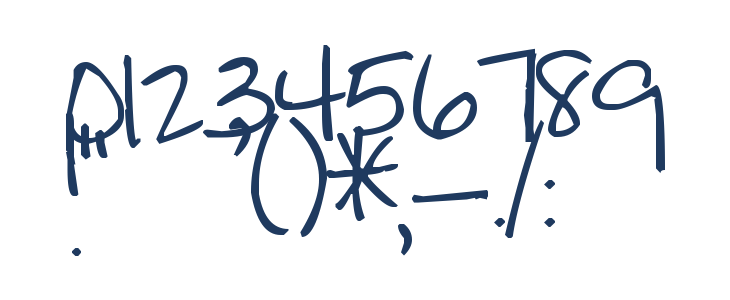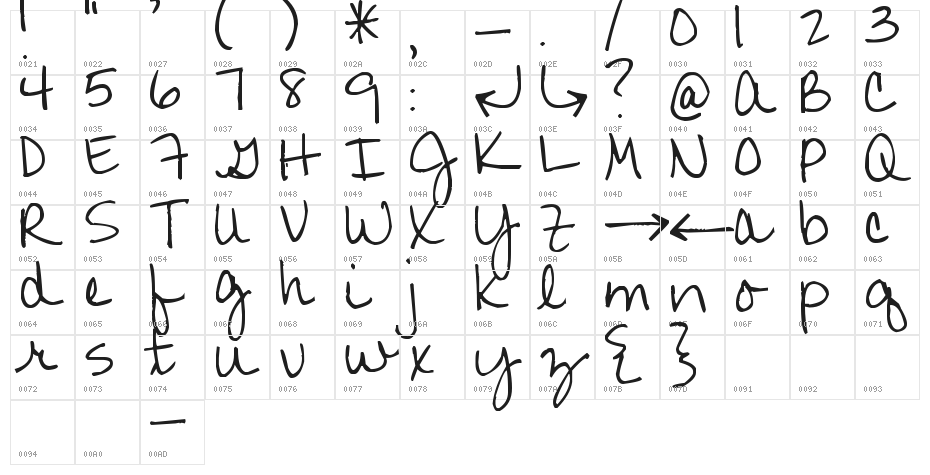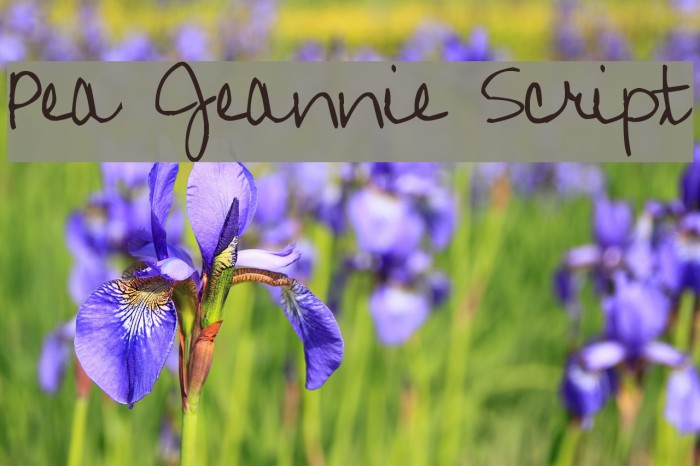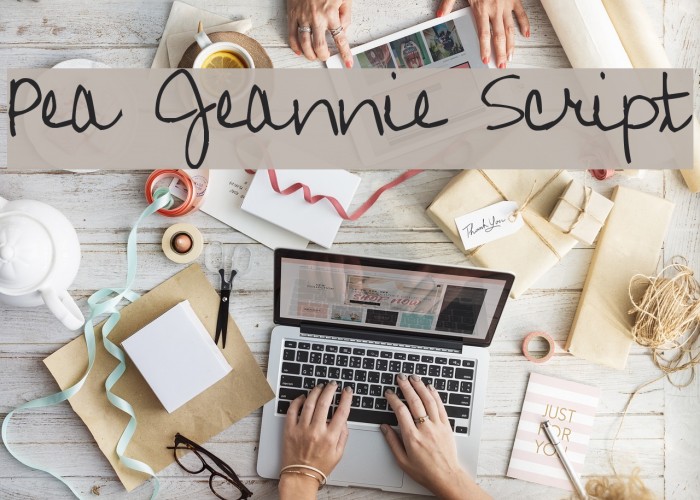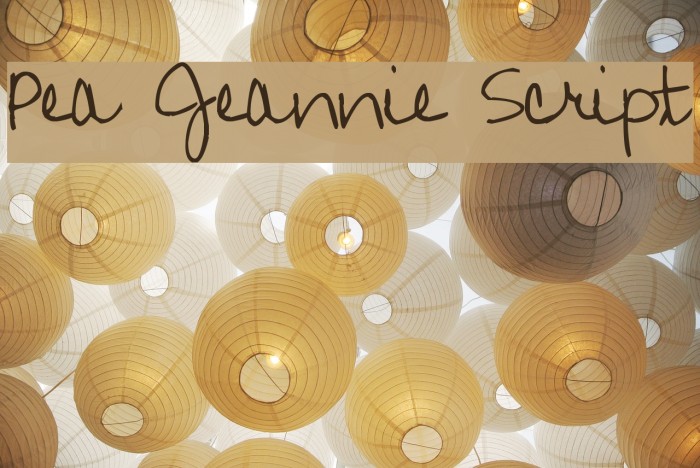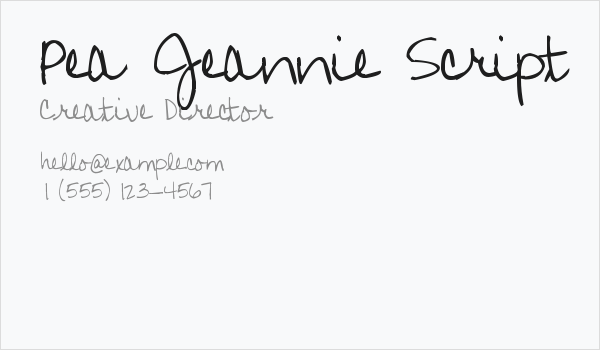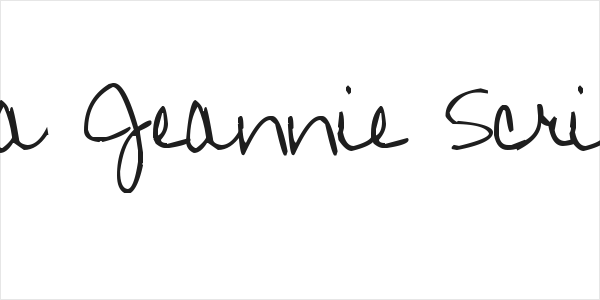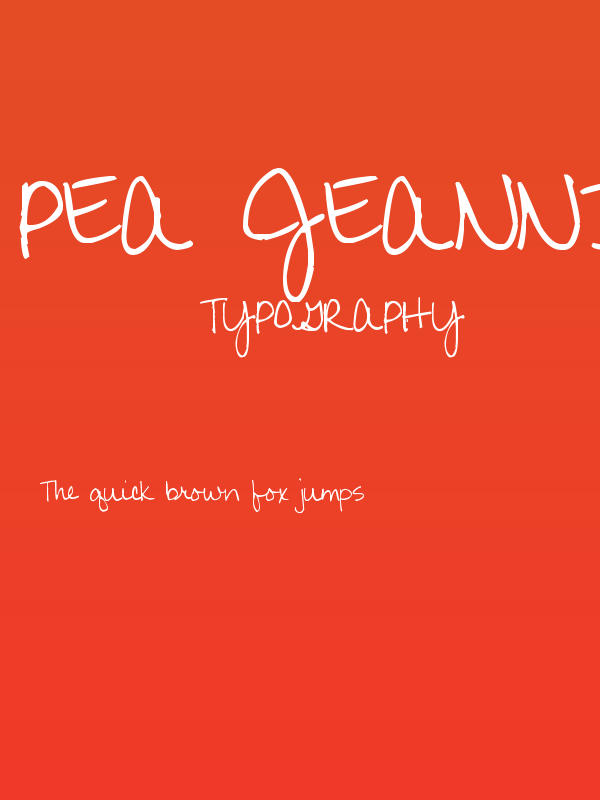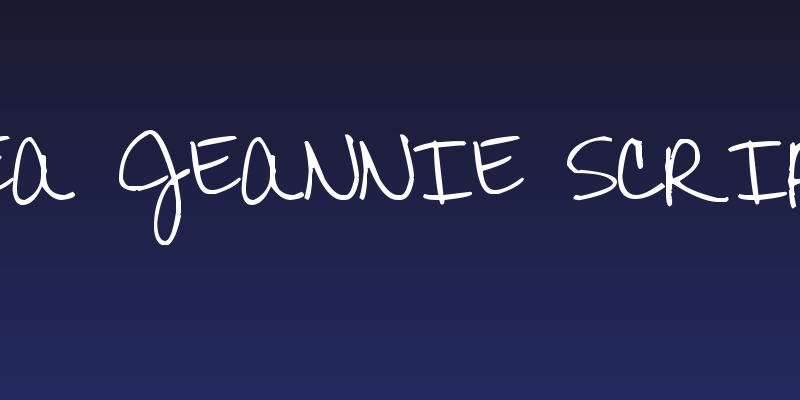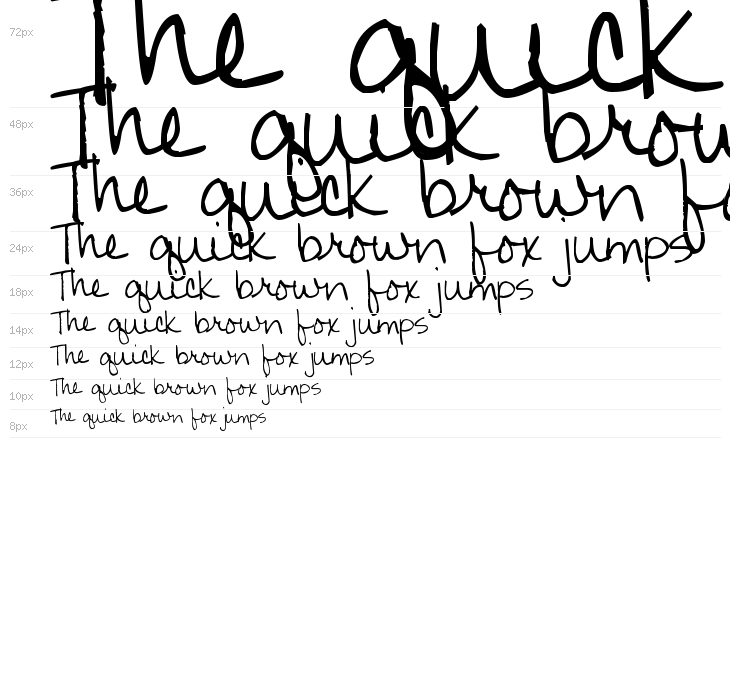
Pea Jeannie Script Font
| Gesamtstil | Casual, Playful |
| Anwendungsfall | Headlines, Informal text, Personal projects |
| Vorgeschlagene Projekte | Ideal for greeting cards, invitations, personal notes, and social media graphics. |